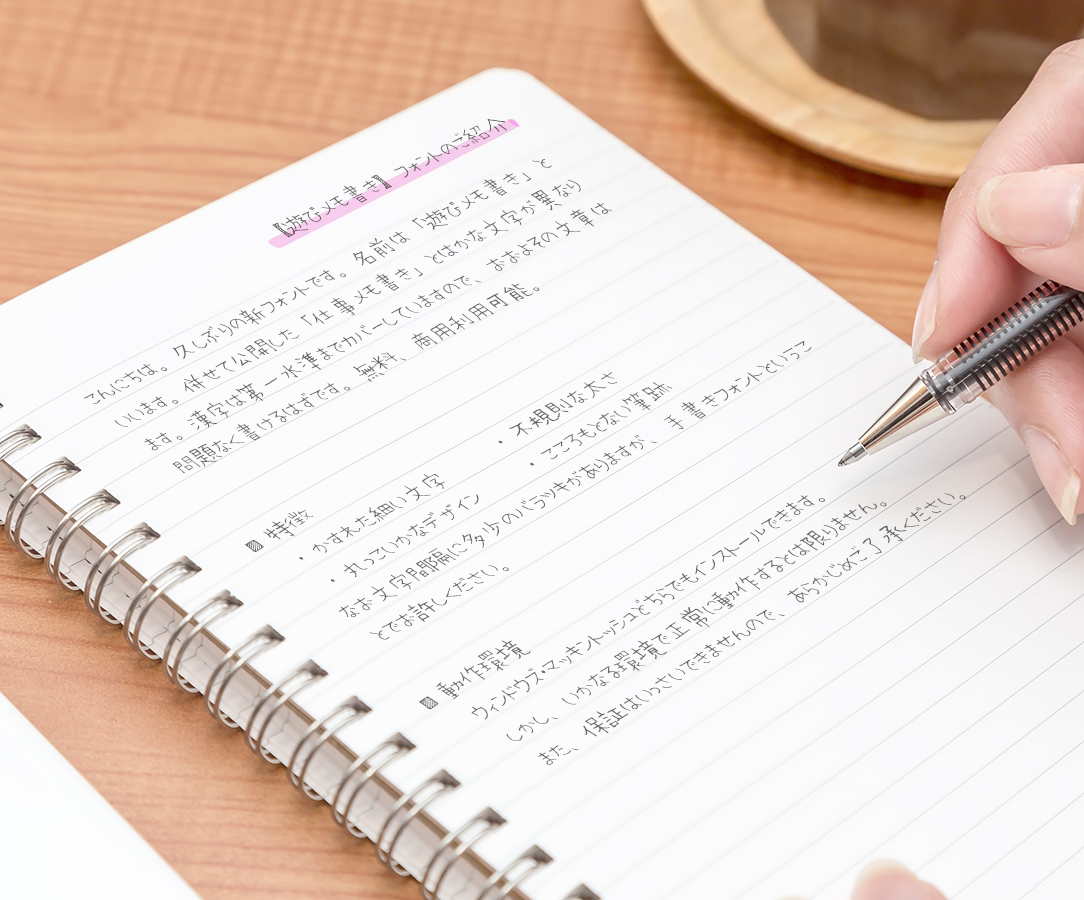
一种名为“Play Memowriting”的免费字体,其外观模糊,看起来像是用细铅笔写的。
它的特点是假名比汉字稍小,
通过调整每个假名字符之间的间距,我们尝试创建更逼真的手写字体。
它还支持最小的垂直书写。
包含的字符 该字体中包含的字符包括假名字符、字母数字字符、符号和一级汉字。
几乎所有日常生活中使用的汉字都包含在内,因此您可以毫无问题地使用它们。
未记录的字符将为空白。